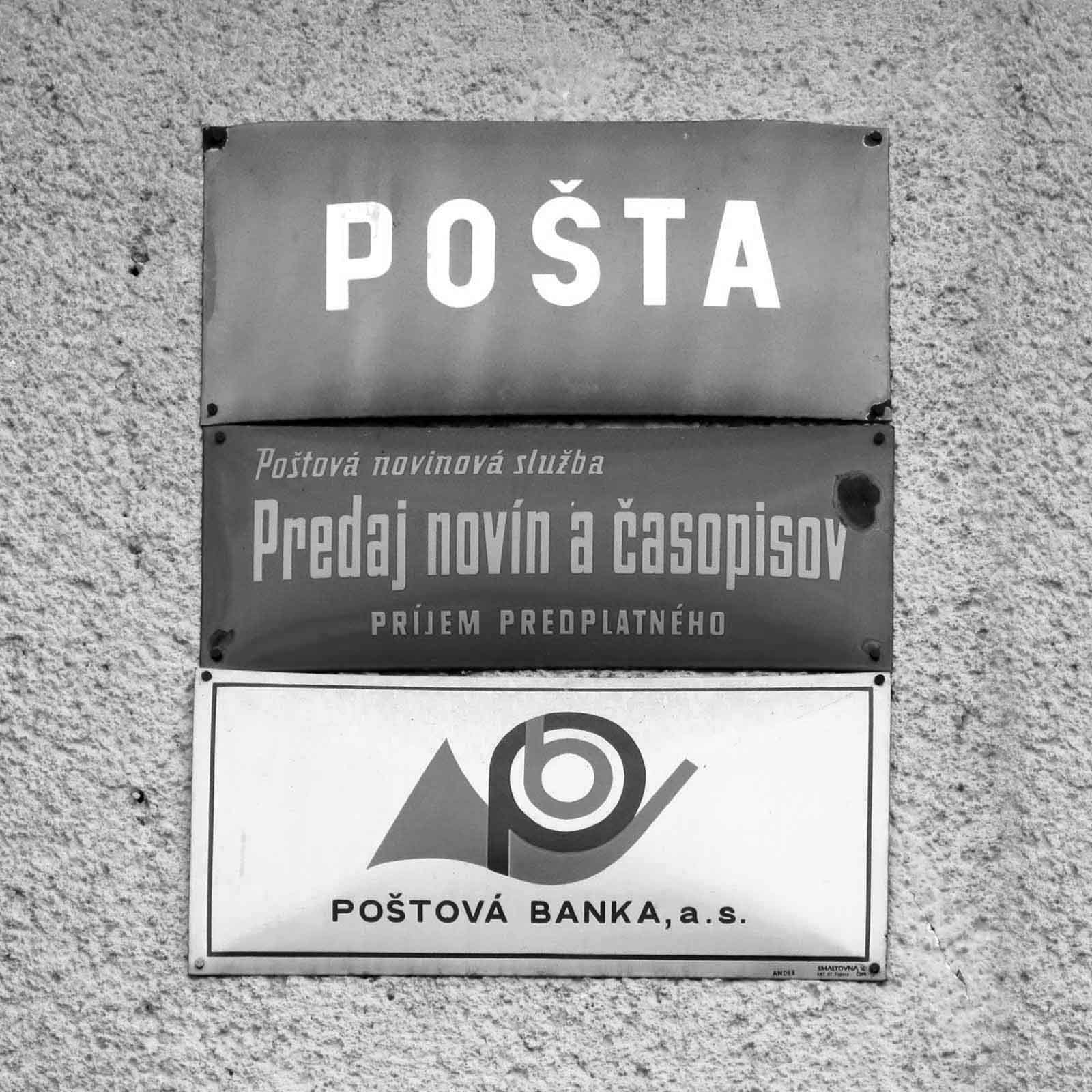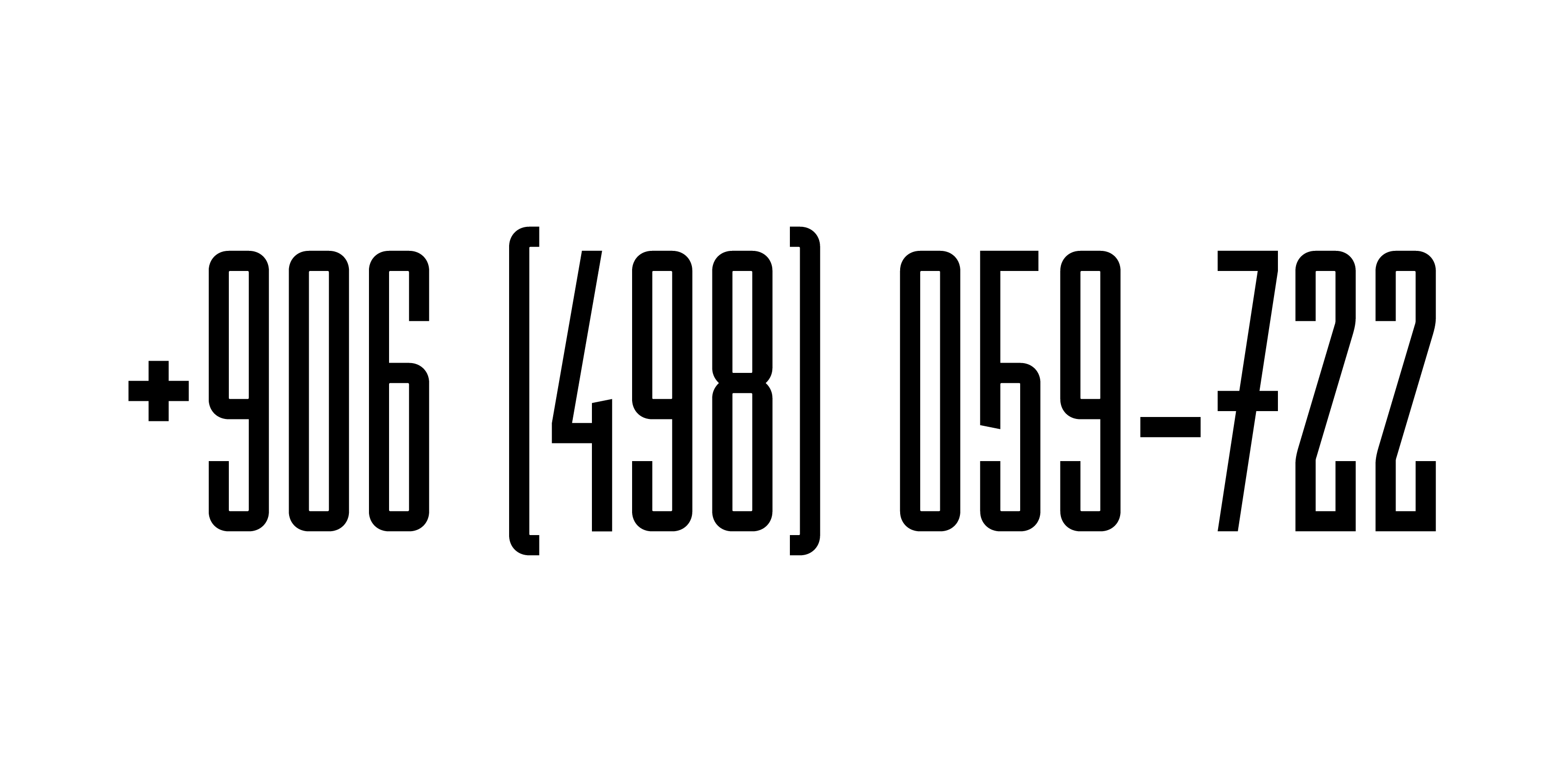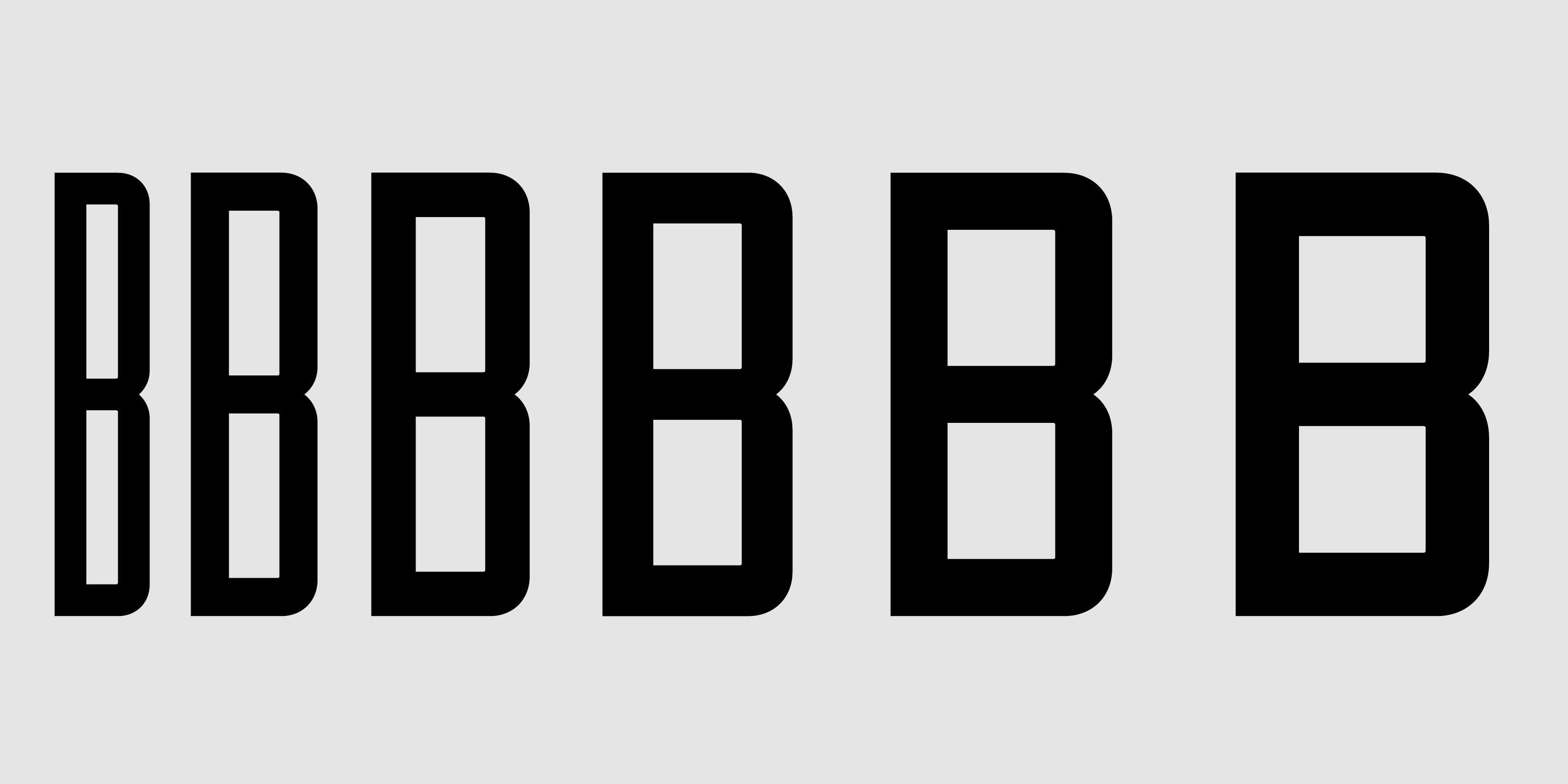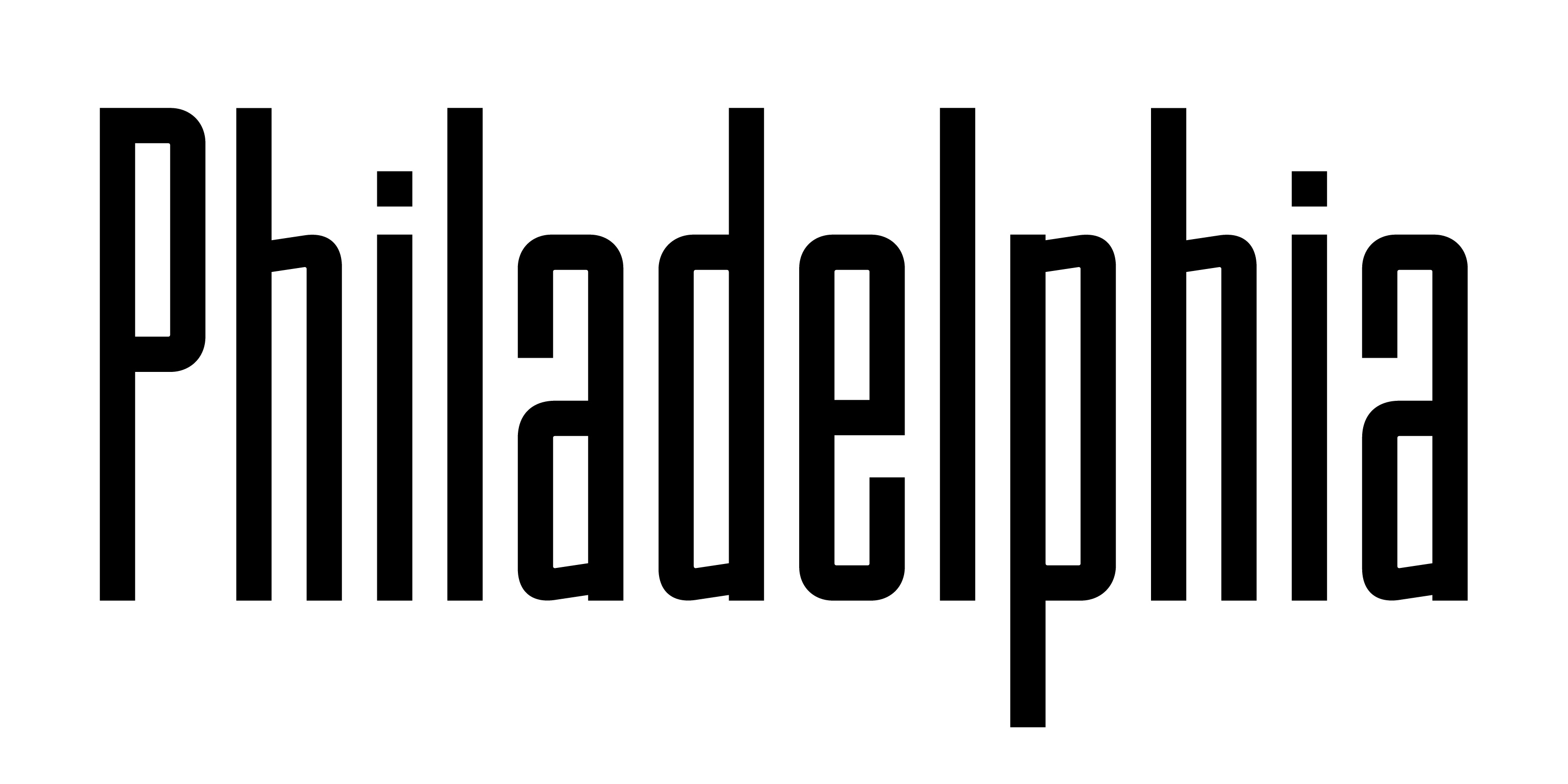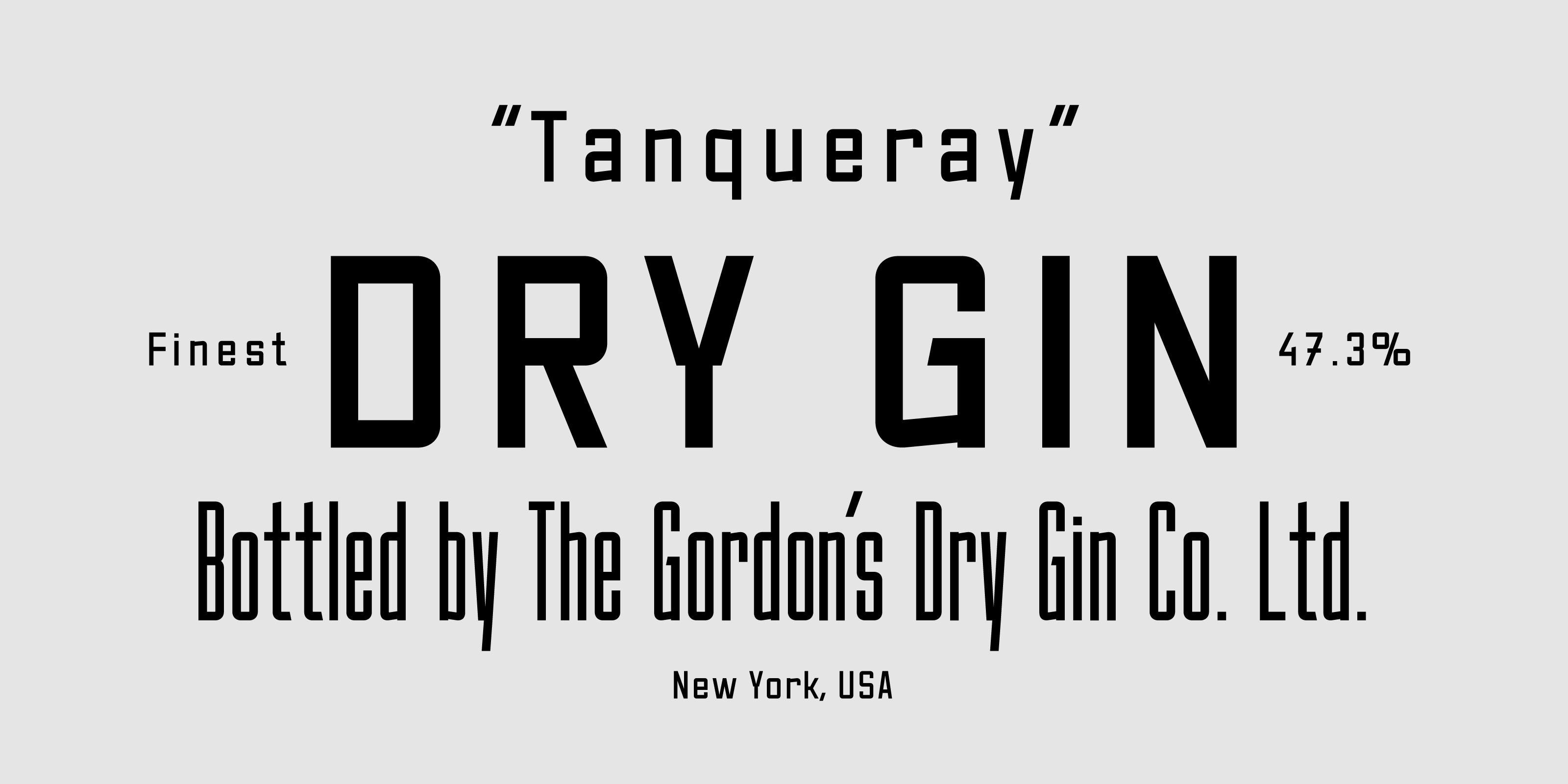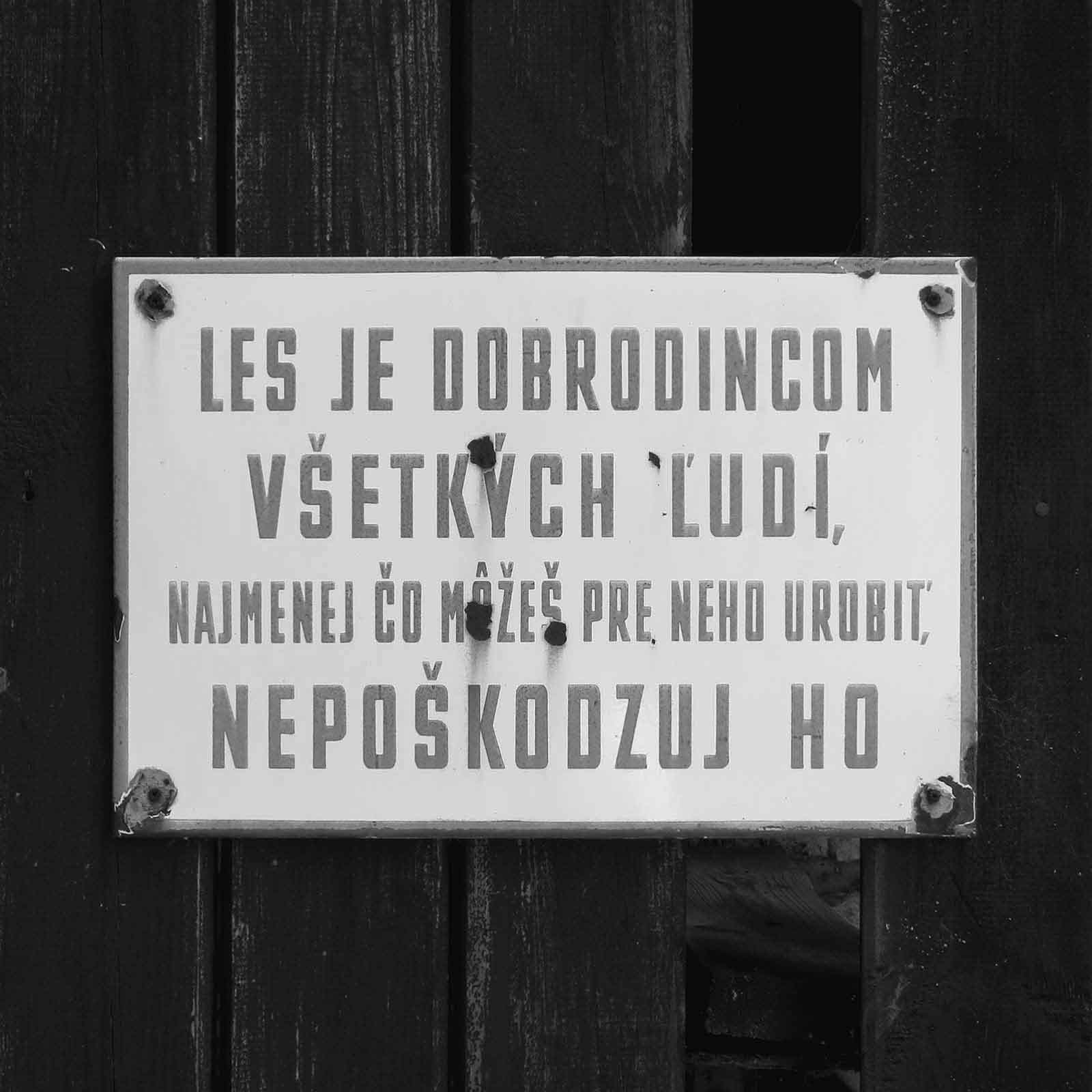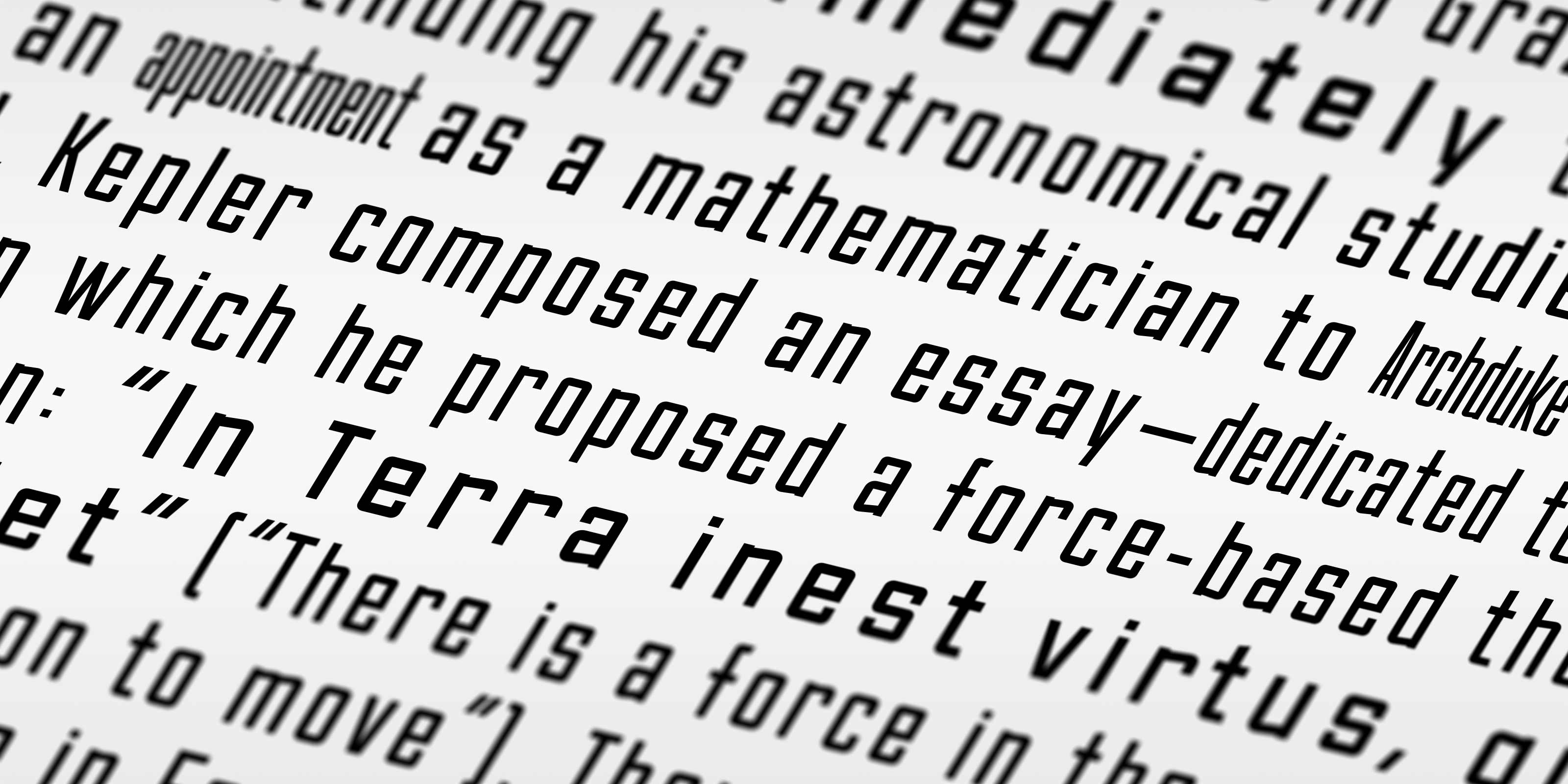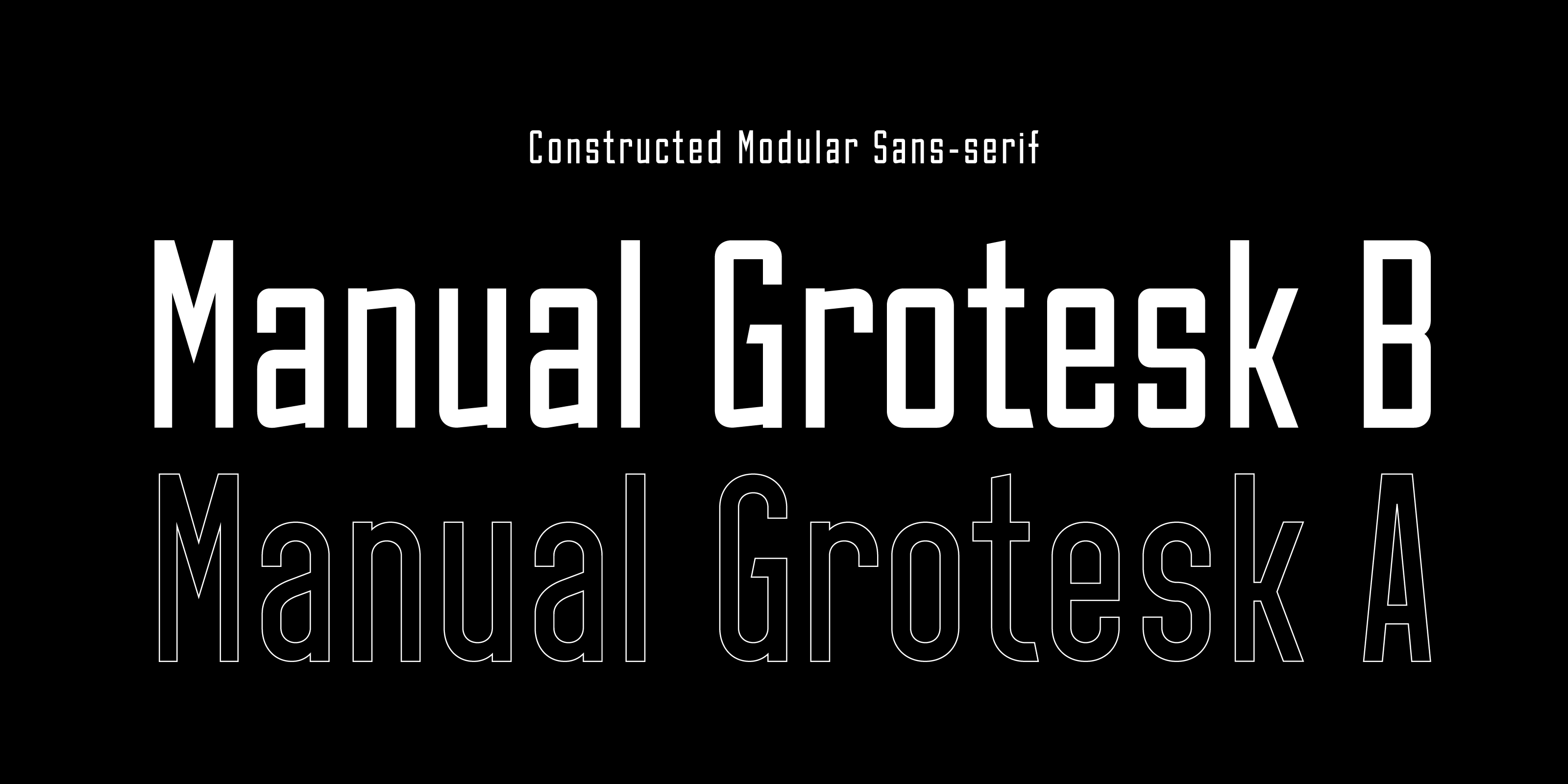
Tradičné písmo z tabuliek verejných budov na Slovensku.
Manual Grotesk B je utilitárne geometrické sans-serifové písmo primárne určené pre použitie v nadpisoch, obsahujúc 6 štýlov, s žiadnym kontrastom, malou šírkou a vysokou strednou výškou.
Podporovanými znakovými sadami písma Manual Grotesk B sú základná latinka a rozšírená latinka, vďaka čomu môže byť písmo použité vo viac ako 100 jazykoch. S celkovým počtom 581 znakov, základnou sadou sú proporčné zarovnané číslice. Funkcie ako štylistická sada 1–6, malé kapitálky, všetky malé kapitálky a ordinály umožňujú ďalšie prispôsobenie a zvyšujú celkovú všestrannosť písma.
Písmo Manual Grotesk B takmer bez akýchkoľvek odchýliek vychádza pôvodnej predlohy ručne konštruovaného písma od Richarda Pípala z polovice 20. storočia.
Toto ikonické písmo, za socializmu prakticky všadeprítomné, je možné dodnes vidieť predovšetkým na starších budovách miestnych samospráv, školách a úradoch, avšak nové tabuľky už ho nepoužívajú. Jeho digitalizácia je preto pokusom o jeho záchranu a zároveň aj snahou spopularizovať ho v novom kontexte.